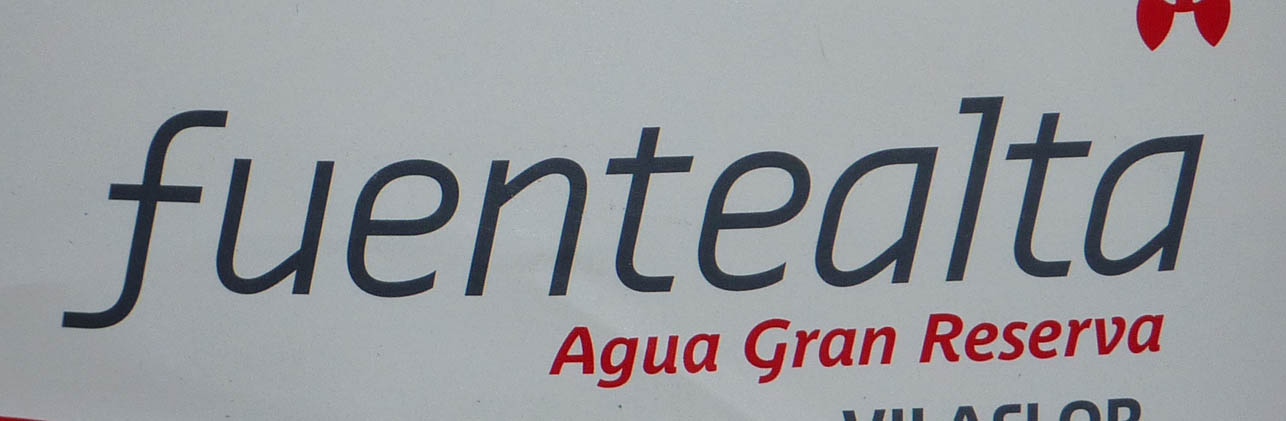
In Spanien ist mir gerade dieses Etikett einer Wasserflasche aufgefallen. Weiß jemand in welcher Schrift das »fuentealta« gesetzt ist? What the font hat mich nicht weiter gebracht. Das »Agua Gran Reserva« ist die Parisine von Jean François Porchez, aber das »fuentealta« paßt nicht. Erkennt das jemand von Euch? Das sieht doch eigentlich ziemlich charakteristisch aus. Ist das auch von Porchez? Und wenn ja was?
Mich hatte es ja ganz spontan an Dino dos Santos’ Schriften erinnert; die Dobra und die Priva gehen etwas in die Richtung. Von den DSType-Schriften ist es aber, soweit ich sehen kann, keine. :?
Ich habe gerade mal hier gestöbert. Ich finde, die Formensprache Deines gesuchten Schriftzuges passt gut zu Porchez, aber von den dort gezeigten Schriften ist es keine, so weit ich sehen kann …